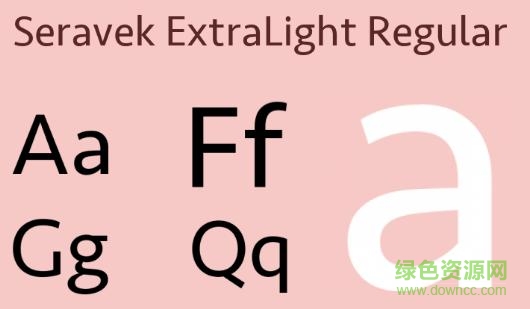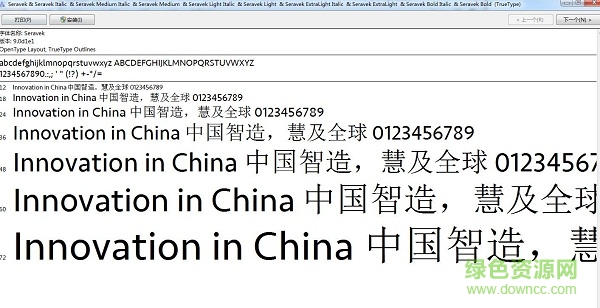
seravek extralight字體是一款極細(xì)的無襯線字體,該字體造型樸素,黑白調(diào)節(jié)均勻,線條流暢,給人感覺非常舒適,從正文排版到網(wǎng)頁設(shè)計均可使用,需要的朋友趕緊下載吧!
拉丁字母字體一般按體系分,每一體系中又有許多體式。體系分為羅馬體體系、哥特體體系、埃及體體系、無飾線體體系、手寫體體系、裝飾體體系、圖形體體系。每種體系里各自又有一些字體。
1.筆畫粗細(xì)對比小,視覺上看起來基本一致;
2.適用于標(biāo)題、廣告,瞬間的識別性高;
3.完全拋棄裝飾襯線,只剩下主干!